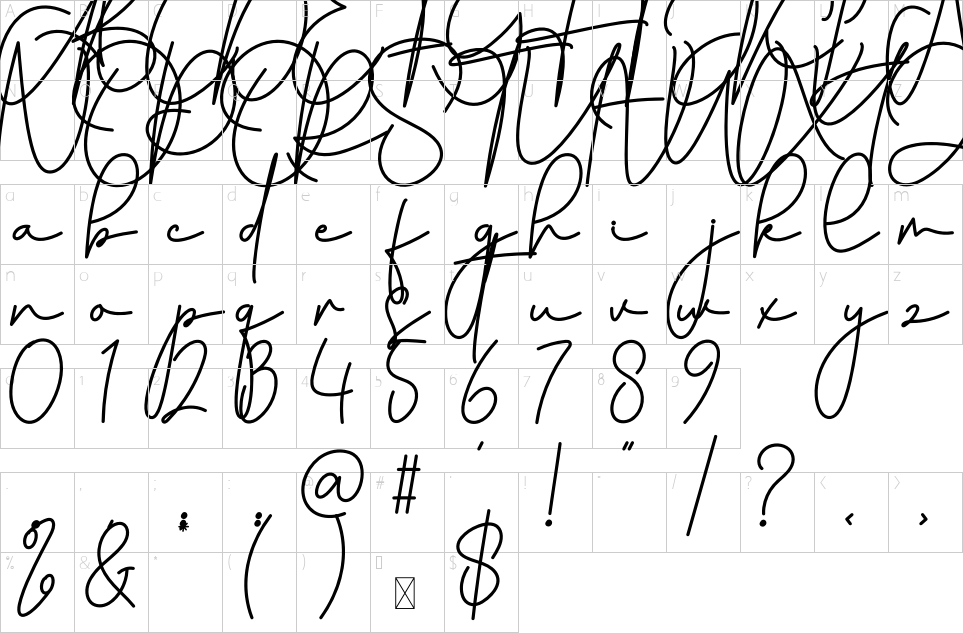
Descubra a elegância e a sofisticação da fonte ‘Margareta Signature’ no seu próximo projeto. Esta fonte foi cuidadosamente projetada por scratchones e já foi baixada por 210 usuários. Com sua tipografia fluida e elegante, você pode criar mensagens profissionais e textos de alto nível. Baixe agora a fonte para Windows e Mac e personalize seu design para alcançar um resultado impecável. Aproveite a variedade de opções de estilo que a ‘Margareta Signature’ oferece para complementar seus trabalhos de design. Descubra por si mesmo o poder dessa fonte única e transforme seus designs em obras de arte.